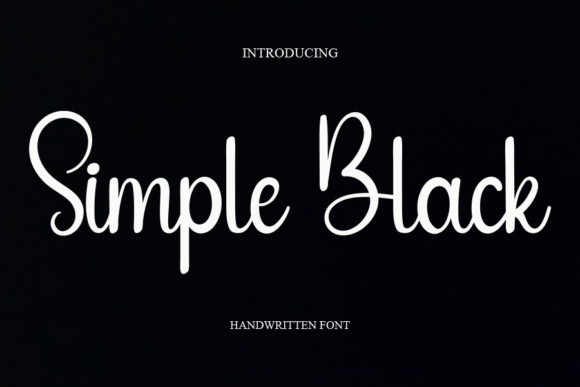
Simple Black
**Simple Black: Uma Fonte Escrita à Mão Perfeita para Tudo!**
Descubra a Charme da Simplicidade com a Simple Black
No mundo da tipografia, há fontes para todos os gostos e estilos. Mas, se você está procurando por algo simples, amigável e fácil de usar, a Simple Black é a escolha perfeita! Esta fonte escrita à mão é ideal para uma variedade de aplicações, desde artesanato até projetos digitais, apresentações e até mesmo cartões de felicitação.
Características da Simple Black
- Tipografia simples e amigável: A Simple Black é uma fonte escrita à mão que consegue transmitir um sentimento de calor e personalidade.
- Uso versátil: Pode ser usada em uma ampla gama de projetos, desde crafts e artesanato até projetos digitais e apresentações.
- Ideal para ocasiões especiais: A Simple Black é perfeita para criar cartões de felicitação, convidados e outros materiais de comunicação para eventos especiais.
- Elegância e simplicidade: A fonte escrita à mão da Simple Black adiciona um toque de elegância e simplicidade a qualquer projeto.
Se você está procurando por uma fonte que seja fácil de usar, simples e perfeita para todas as ocasiões, a Simple Black é a escolha certa! Experimente agora e descubra o potencial da Simple Black em seu próximo projeto!